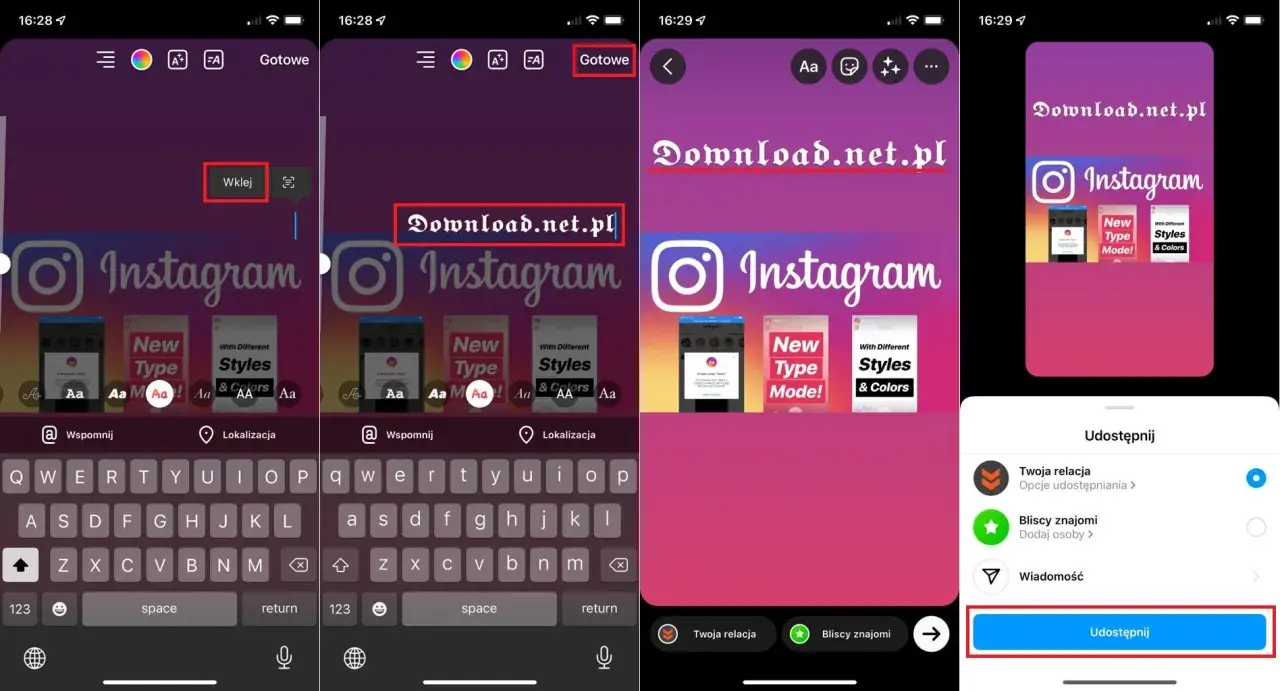
Estetyczny tekst na Instagramie działa najlepiej wtedy, gdy nie udaje ozdoby za wszelką cenę, tylko wzmacnia charakter profilu. Dobre ładne czcionki na ig pomagają wyróżnić bio, uporządkować stories i nadać marce spójny ton, ale tylko wtedy, gdy są czytelne, pasują do branży i nie rozpraszają odbiorcy. W tym tekście pokazuję, które style rzeczywiście wyglądają dobrze, gdzie mają sens i jak ich używać, żeby profil był bardziej dopracowany, a nie przeładowany.
Najlepszy efekt daje prosty styl, jeden wyraźny akcent i pełna czytelność
- Na Instagramie najlepiej sprawdzają się style, które da się odczytać w kilka sekund na telefonie.
- Większość „fontów” do wklejenia to nie prawdziwe kroje pisma, tylko znaki Unicode wyglądające jak font.
- Do bio i highlightów wybieram zwykle jeden neutralny styl i jeden dekoracyjny akcent, nie więcej.
- Najbezpieczniejsze są prosty sans, elegancki serif, small caps i umiarkowana kursywa.
- Ozdobne znaki, gothic i mocne warianty glitch zostawiam na pojedyncze wyróżnienia, nie na cały profil.
- Przed publikacją zawsze sprawdzam tekst na ekranie telefonu, bo to, co wygląda dobrze na komputerze, bywa męczące na mobile.
Jakie style liter na Instagramie wyglądają najlepiej
W praktyce większość „instagramowych fontów” to nie klasyczne fonty instalowane w systemie, tylko stylizowane znaki Unicode. To ważne rozróżnienie, bo taki tekst działa w bio, podpisach czy nazwach highlightów, ale jego jakość zależy od czytelności, urządzenia i miejsca użycia. Ja patrzę na to nie jak na sztuczkę, tylko jak na narzędzie do budowania wrażenia.
| Styl | Najlepsze zastosowanie | Efekt | Ryzyko |
|---|---|---|---|
| Prosty sans / bold | Bio, CTA, okładki rolek, komunikaty promocyjne | Czystość, nowoczesność, wysoka czytelność | Może wyglądać zbyt zwyczajnie, jeśli nie ma żadnego akcentu |
| Szeryfowy serif | Beauty, butik, premium usługi, editorial look | Elegancja, miękkość, bardziej „redakcyjny” klimat | Przy małym rozmiarze bywa cięższy i mniej lekki |
| Kursywa / handwritten | Krótki cytat, podpis, osobista marka, storytelling | Ciepło, ludzki ton, wrażenie ręcznego zapisu | Za długa treść staje się męcząca i rozmyta |
| Small caps | Highlighty, nazwy sekcji, mini nagłówki | Porządek, subtelna elegancja, spójność | Przy cienkich wariantach może znikać na jasnym tle |
| Condensed bold | Promocje, wyprzedaże, terminy, mocne nagłówki | Energia, szybkie przyciąganie uwagi | Łatwo przesadzić i zrobić z profilu krzykliwą tablicę ogłoszeń |
| Gothic / blackletter | Niszowe kampanie, mocny klimat, projekty tematyczne | Charakter, wyrazistość, styl „statement” | Słaba czytelność i wyższe ryzyko, że odbiorca po prostu odpuści |
Jeśli mam wskazać jedną zasadę, to jest nią dobór stylu do roli tekstu, a nie do samej estetyki. Styl może być ładny, ale jeśli odbiorca nie zrozumie go od razu, traci sens. Z tej perspektywy najpewniejsze są kroje proste, a ozdobne traktuję jak przyprawę, nie jak danie główne. To prowadzi do pytania, gdzie konkretnie taki tekst daje najlepszy efekt.
Gdzie ozdobna typografia działa najlepiej na profilu
Na Instagramie nie ma jednego miejsca, w którym każdy styl zadziała tak samo dobrze. Bio, stories, podpisy i okładki rolek mają inną funkcję, więc inaczej znoszą eksperymenty. W praktyce najbardziej opłaca się stosować różne style tam, gdzie mają realnie pomóc w odczytaniu lub zapamiętaniu treści.
- Bio - tu najlepiej działa prosty styl z jednym akcentem. Wystarczą 2-4 krótkie linie, bo bio ma być czytelne w sekundę, a nie dekoracyjne na siłę.
- Stories - dobrze wyglądają krótkie nagłówki w boldzie, serifie albo small caps. Dłuższy tekst lepiej zostawić w prostym kroju, bo na ekranie telefonu szybko się męczy.
- Podpisy pod postami - tutaj zwykle wygrywa neutralna typografia z jednym mocniejszym początkiem. Ja stosuję akcent tylko w pierwszej linii albo w wezwaniu do działania.
- Okładki rolek - sprawdzają się style wyraźne, kontrastowe i szeroko czytelne, najlepiej bez wielu ozdobników. Tytuł ma „zatrzymać palec”, nie udawać projektu modowego magazynu.
- Highlighty - small caps, prosty serif albo krótki bold dają efekt dopracowanego profilu. Tu najlepiej działają nazwy 1-2 wyrazowe.
- Promocje i oferty - condensed bold lub wyraźny sans ułatwiają szybkie skanowanie informacji, zwłaszcza gdy trzeba pokazać datę, rabat albo limit miejsc.
Ja zwykle ustawiam hierarchię tak: najpierw czytelność, potem styl, na końcu efekt „wow”. To brzmi mniej efektownie niż modne hasła o estetyce, ale właśnie taki układ najczęściej sprzedaje się najlepiej w profilu marki lokalnej. A skoro mowa o markach, czas przejść do tego, jak dopasować styl do branży i charakteru biznesu.
Jak dopasować styl do marki i branży
Dla lokalnego biznesu typografia na Instagramie nie jest detalem. To część pierwszego wrażenia, które użytkownik buduje jeszcze przed wejściem w ofertę, cennik czy wiadomość prywatną. Dobrze dobrane litery mogą podbić profesjonalizm, a źle dobrane sprawiają, że profil wygląda chaotycznie albo zbyt młodzieżowo względem oferty.
Jeśli chcesz zacząć od jednego ruchu, wybierz dziś jeden styl bazowy i jeden akcent, a potem sprawdź, czy profil nadal wygląda dobrze po stronie telefonu. To zwykle wystarcza, żeby odróżnić estetyczny profil od przypadkowo ozdobionego.